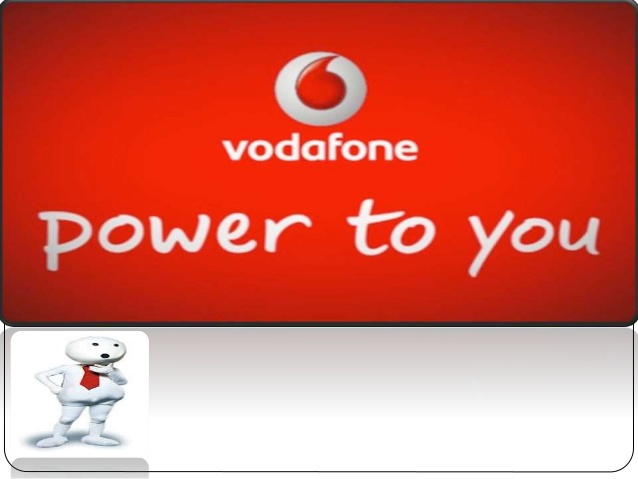
Vodafone: power to you
kann mir bitte jmd sagen welcher Font der Schriftzug "power to you" auf dem alten Logo von Vodafone geschrieben ist?
die drei unterschiedlichen o lassen den Schluss zu, dass das (ursprünglich) handgeschrieben ist.
Die gemeinen "O"s sind alle leicht unterschiedlich – ich würde von einem speziell für den Claim entworfenen (geschriebenen) Schriftzug ausgehen.